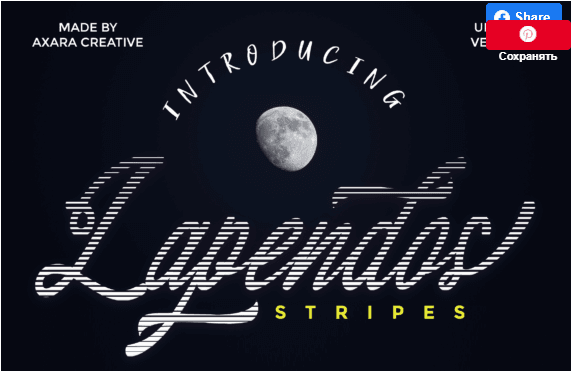
Lapendos Stripes Font
Lapendos Stripes — забавный и смелый дисплейный шрифт с уникальными полосками. Получите вдохновение от этого привлекательного шрифта!